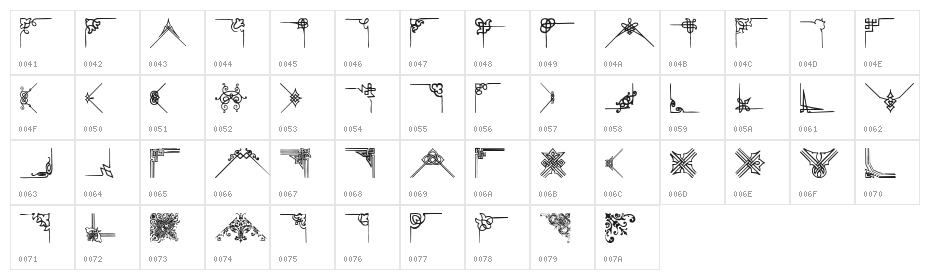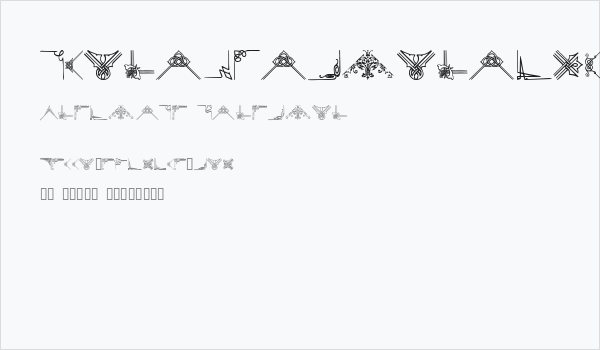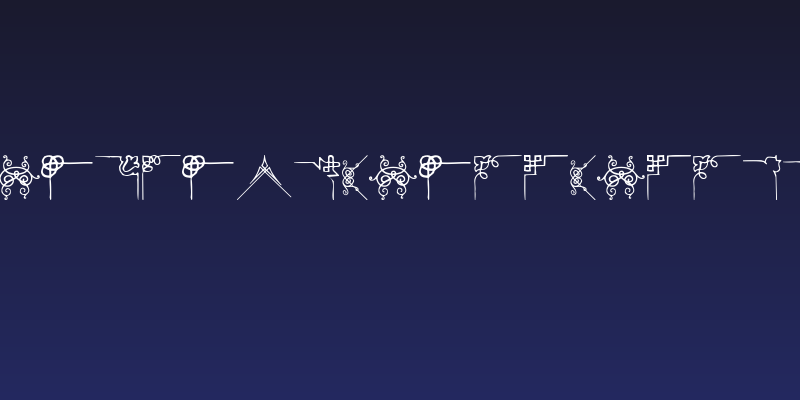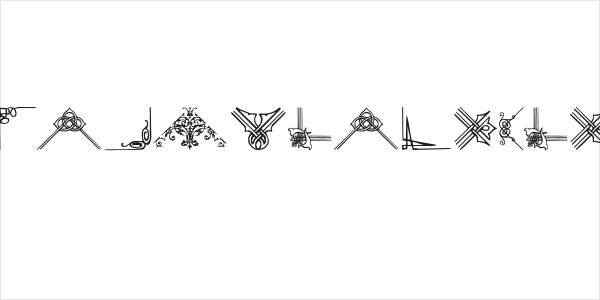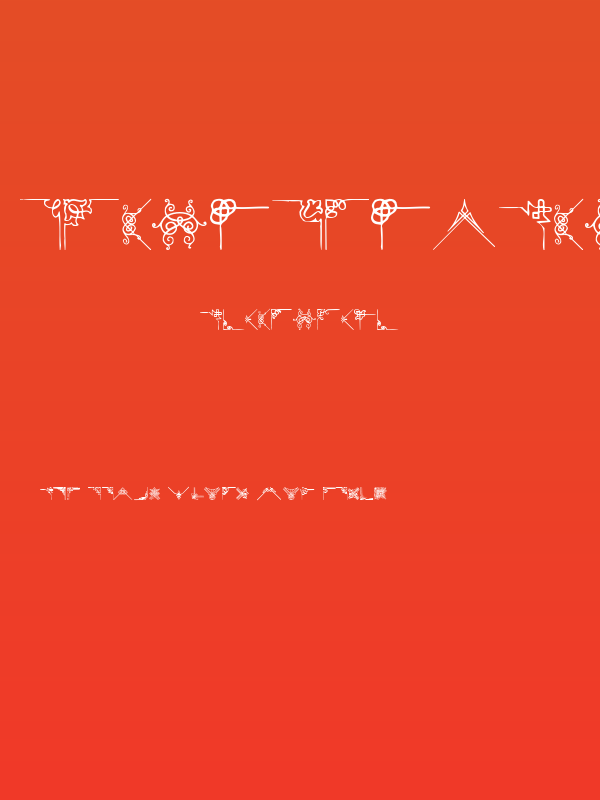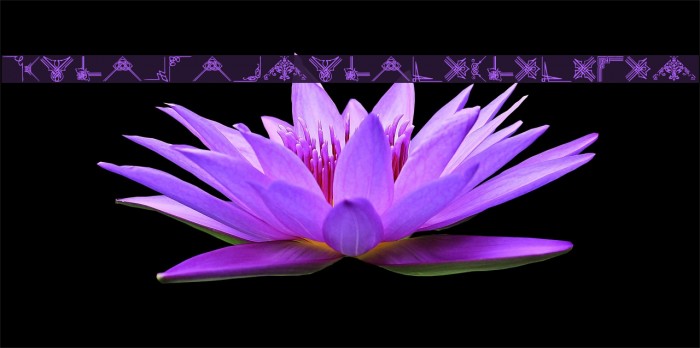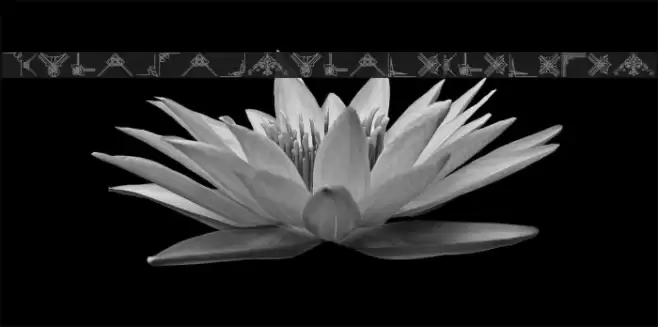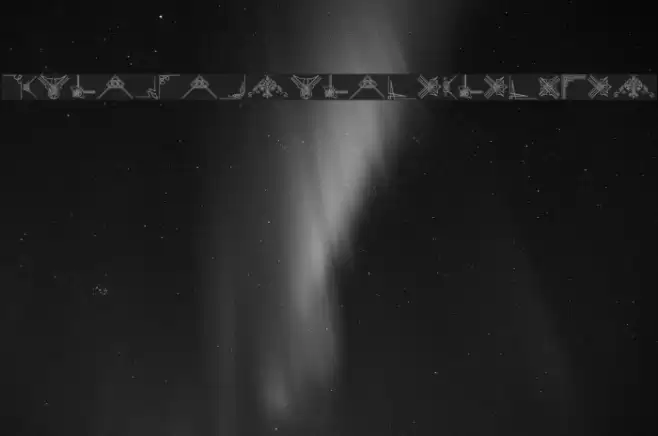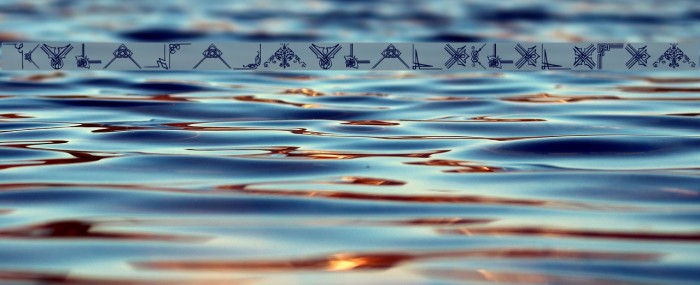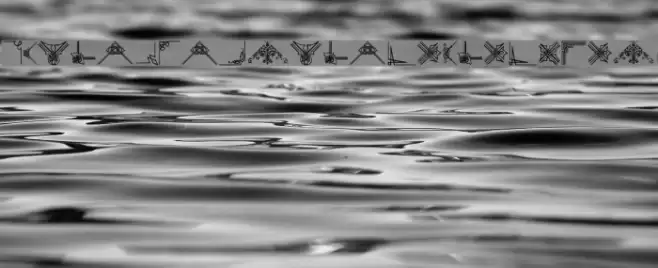
FloridVictorianOrnament Font
✎ Decorative
| النمط العام | Vintage |
| حالة الاستخدام | Decorative elements, not suitable for text. |
| مشاريع مقترحة | Ideal for vintage-themed invitations, decorative borders for print materials, or as embellishments in graphic design projects. |